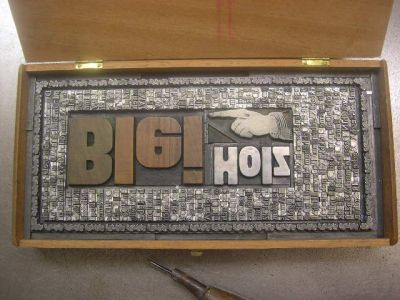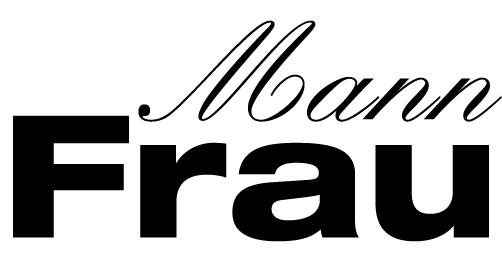
Typografie ganz einfach
in unserer kleinen Agentur bekommen wir regelmaßig Besuch von Schulpraktikanten. Das ist immer eine schöne Abwechslung und auch Herausvorderung. Inzwischen habe ich einige gestalterische Quasi-Aufgaben erstellt, um ein objektiveres Bild von den Fähigkeiten zu bekommen.
Nun stellt sich immer noch das Problem einem so jungen Menschen die Bedeutung im Einsatz von Schrift nahe zu bringen.
Hier wird gern gesperrt, gemischt und – für mich – zusammenhangslos gesetzt, dass ich gern eine spielerische Variante der Schriftgestaltung suche, um den Sinn für Typografie zu schärfen.
Mit Worten und Fachtheorie will ich gar nicht erst anfangen, um Blockaden zu vermeiden. Der direkte Vergleich eines schlecht und eines gut gesetzten Textes führt auch zu keinem Aha-Erlebnis. Den Unterschied zwischen Arial und Helvetica erschließt sich dem ungeübten Schülerauge ebenso wenig. Für viele von ihnen sind Schriften Allgemeingut, welche kostenlos vom PC-Hersteller kommen. Das Schriften von einem echten Menschen gestaltet wurden ruft oft Erstaunen hervor, erst recht der Zusatz, dass der Gestalter sich bewusst etwas dabei gedacht hat.
Hat jemand von euch schöne Ideen, evtl. aus einem Workshop, wie sich Typografie und gerade die Besonderheiten und die Wertschätzung vermitteln lassen. Wo fängt man am besten an sich mit Schrift zu beschäftigen? Wie nähert man sich dem Thema Typografie spielerisch?
Das Thema interesssiert mich auch. Bei uns die gleiche Lage. Mein Eindruck ist inzwischen, dass man für das Thema Typografie geboren sein muss. Selbst auszubildende Mediengestalter hatten nach 2 Jahren weder Feeling noch Interesse, es zu bekommen. Wie begeistert man Menschen dafür?
Bei uns geht kein Schülerpraktikant ohne seine eigene Schrift wieder nach Hause.
Ich habe ein Handfont-Formular von Fontshop (PDF zum runterladen). Das wird ausgefüllt und dann gescannt. Los gehts. Im Laufe der nächsten zwei oder drei Tage ergeben sich dann eine Menge Fragen bei der Arbeit mit dem Programm Fontographer. Wenn die ersten Zeilen mit der eigenen Schrift gesetzt werden ist das hallo! dann groß.
Auf diese Art und Weise bin ich inzwischen zu einem ganz beachtlichen Archiv von Halbstarken-Handschriften gekommen. :)
Diese meine Antwort stammt eigentlich nicht von mir, sondern wurde von Lehrern von Fachschulen für Typographie vermittelt:
Ein sehr gutes Mittel, um Laien und gerade jungen Laien Typographie, Schrift und deren Möglichkeiten nahezubringen, ist der Bleisatz. Hier muß nicht abstrakt gedacht werden wie an einem Bildschirm-Arbeitsplatz, sondern man hat etwas zum Anfassen. Kann verschieben, etwas fällt um, man muß es wieder aufstellen.
Und dann kann man Farbe draufschmieren, ein Blatt Papier darauf legen und mit einer "Nudel" (kleine Abziehpresse) darüber rubbeln. Und hält dann ein Ergebnis in Händen... Der Aha-Effekt und der Stolz "Das habe ICH gemacht" ist jedesmal wieder überraschend.
In den letzten Jahren habe ich bestimmt schon ein Dutzend solcher "Grunsausstattungen" für Pädagogen, aber auch Firmen aus der Druckindustrie zusammengestellt und geliefert.
Man denkt immer, man brauche soviel dafür, aber das ist nicht richtig.
- Eine Spindelpresse - ca. 50 Euro bei Ebay
- 2 Satzschiffe
- 1 Winkelhaken
- 1 Ahle
- 1 Schließrahmen DIN A5
- 2 Schließzeuge und ein paar Schließstege
- 1 Schrift 24 p
- 5 kg Blindmaterial (Ausschluß und Regletten)
- 1 Handwalze
- 1 Tube Farbe (oder eine Offsetfarbe geht auch)
- 1 Flasche Walzenwaschmittel aus der Druckerei
Kostet alles in allem vielleicht 120-150 Euro.
Fröhlich winkend...
konntest du sie dennoch begeistern? Oder war das eher ein Krampf.
ein krampf war das nicht, sie haben gemrkt wie stark eine schrift sein kann,
sie haben schriften den richtigen unternehmen zugeordnet und waren
erstaunt, dass es so fest im kopf sitzt.
ja, dieses unternehmen zuordnen macht eigentlich spaß.
also einfach mal so paar beispiele die zeigen wie stark typografie
sein kann. werbeanzeigen ohne logo, von mercedes, marlboro,
nivea, usw. weißt du was ich meine? ich finde gerade keine beispiele.